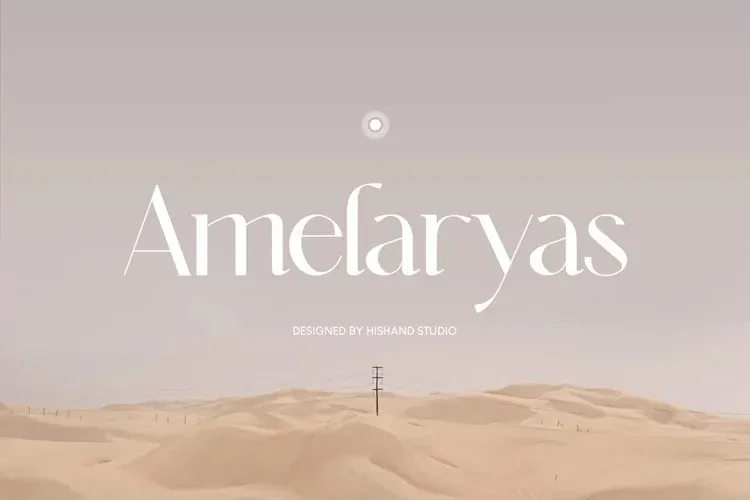
Amelaryas Font
A fonte ‘Amelaryas Font’ é uma tipografia sans serif que se destaca por seu estilo elegante e moderno. Ela conta com ligaturas alternativas e novos elementos, proporcionando um acabamento premium para qualquer projeto gráfico. Feita pelo estúdio de designer Hishand Studio, a fonte apresenta linhas finas e limpas que tornam-a adequada não apenas para criar logomarcas e identidades visuais, mas também para trabalhos como design de convites, embalagens de papelaria, decoração de casamentos, posts nas redes sociais, e muito mais. A simplicidade deste tipo de fonte se encaixa perfeitamente em ambientes digitais onde a legibilidade é crucial, enquanto mantém um toque sofisticado que certamente chamará atenção quando você precisar destacar algo no design. Este é o tipo certo para criar uma impressão forte e profissional em qualquer projeto.